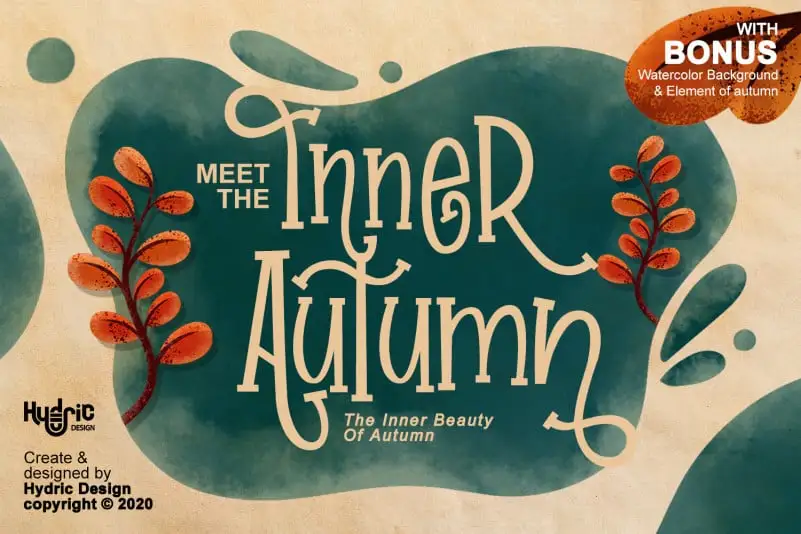
Inner Autumn Display Font – Download Grátis
Inner Autumn Display Font é uma fonte exibição que reflete a beleza interior no período da primavera tardia. Inspirada num conto infantil sobre a pureza do amor por essa estação, esta fonte de exibição traz um aspecto descontraído e cindado que oferece um ambiente místico e mágico para seus projetos gráficos. Perfeita tanto para títulos em livros ou histórias de aventura, logomarcas e identidades, postagens nas mídias sociais, anúncios e designs de produtos, a Inner Autumn Display Font traz um toque especial às suas criações. Sempre surpreendente e versátil, ela pode ser usada em diversos contextos que exigem uma nota especial para sua identidade visual ou design de marca.